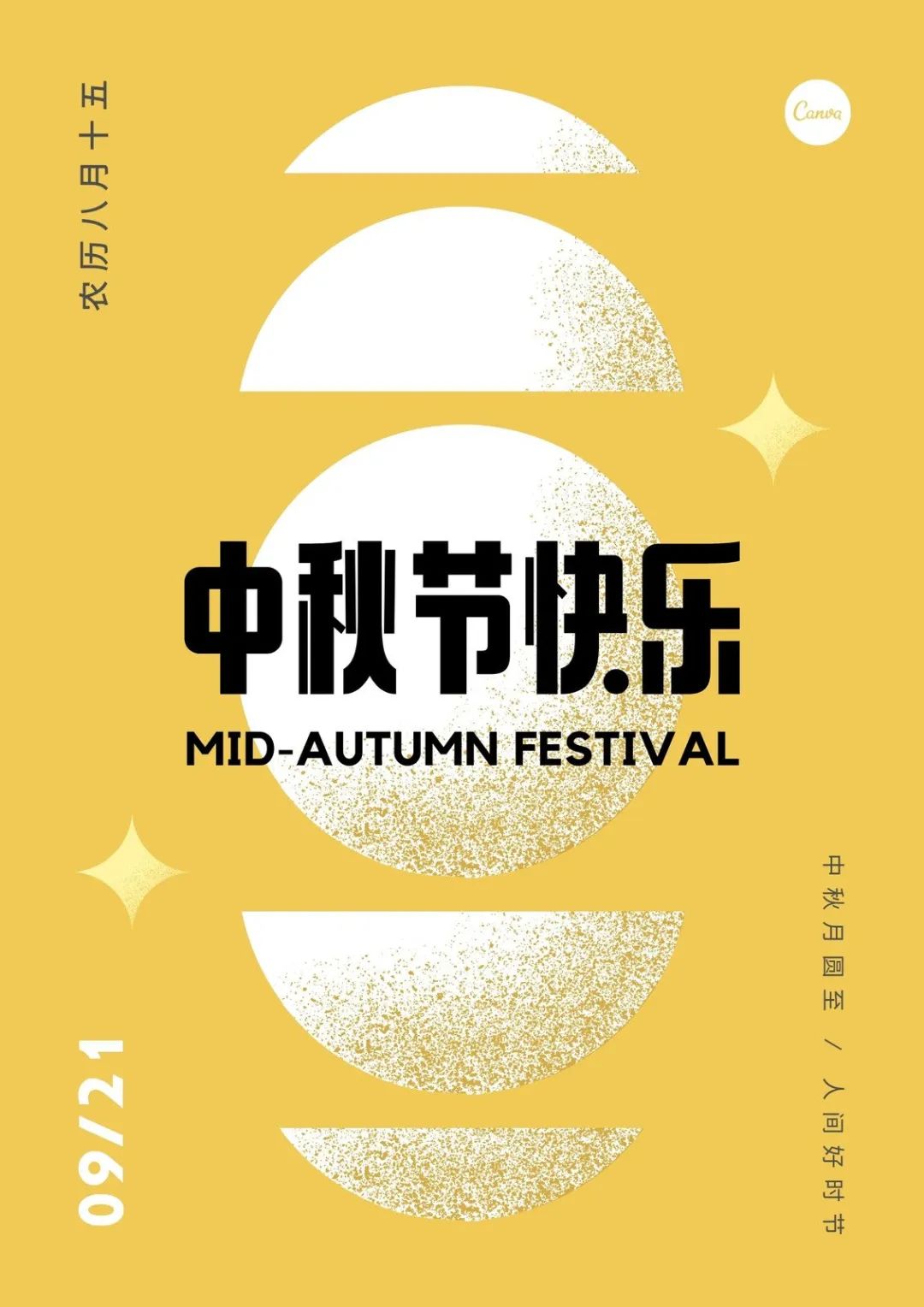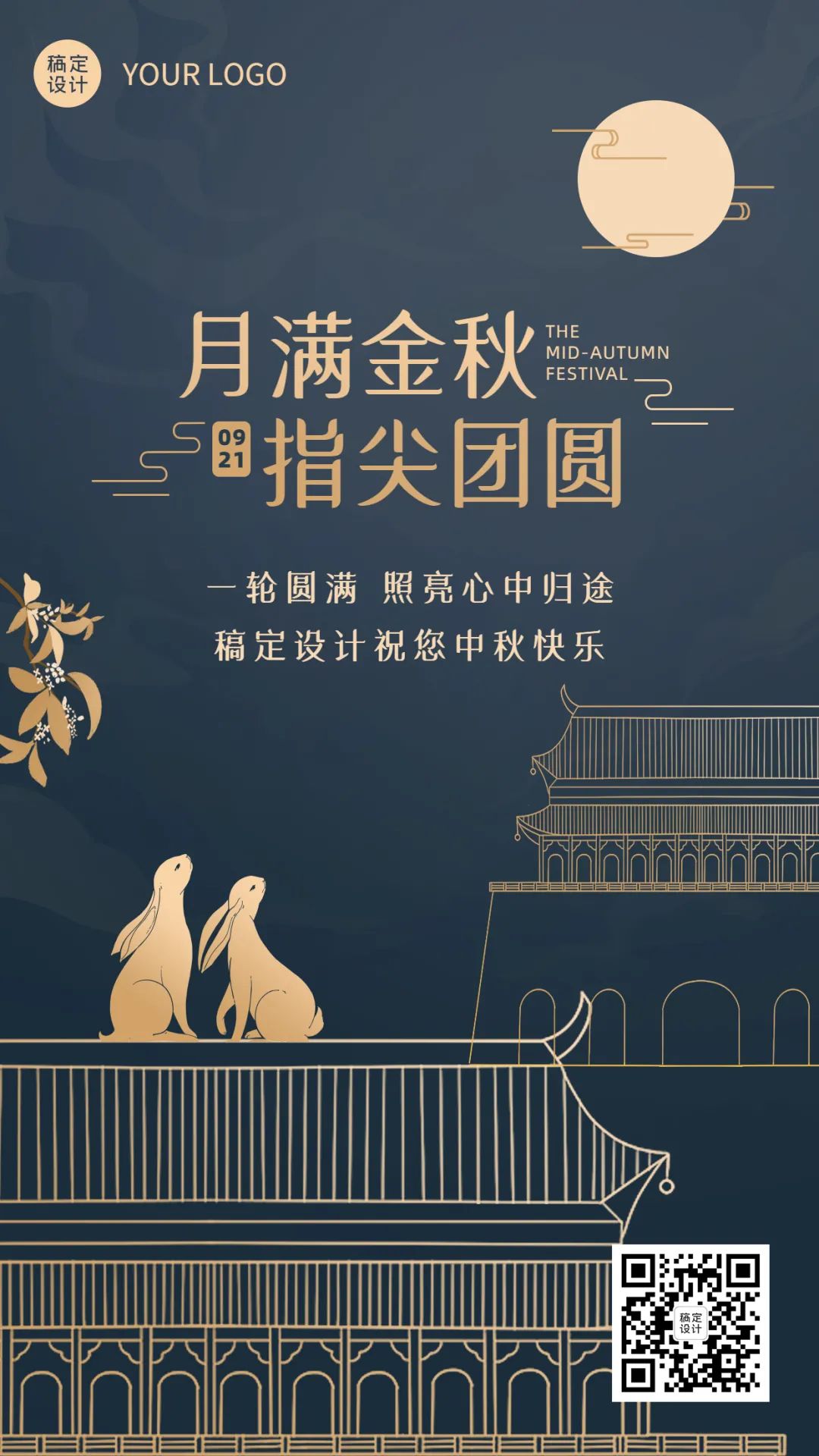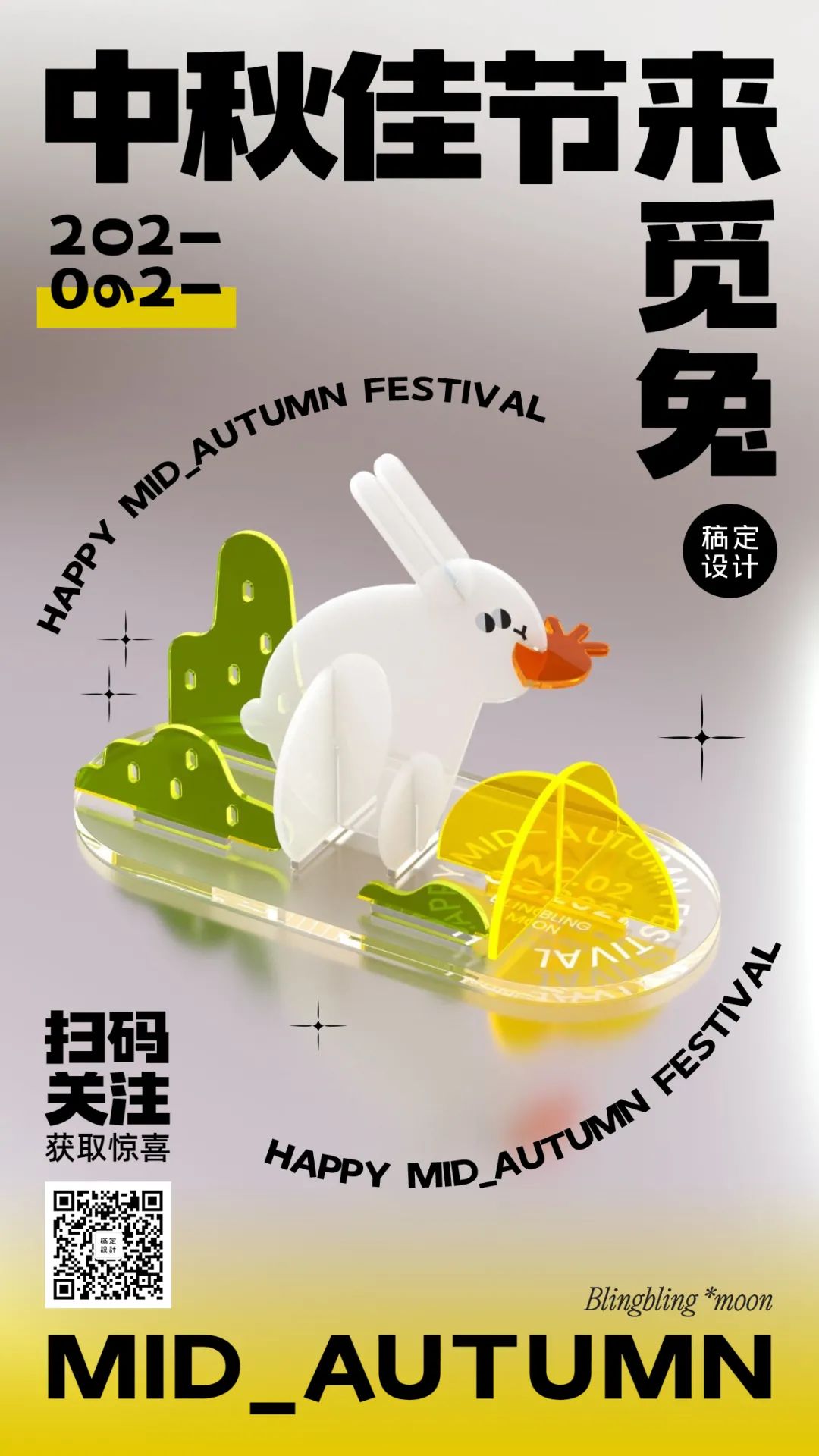
适合中秋国庆的字体大全
眼看着马上就中秋了,紧接着又是国庆,可是柚子却高兴不起来,一是抢不到北京环球影城的VIP门票(注定要家里躺平了),二是还有很多图要做啊(如果不想加班的话),想想就脑阔痛……
那说回马上就要交作业的中秋,如果你想走古典路线,可以选择传统的楷书、隶书、毛笔字等。
如果想别出心裁一点,可以选择更有个性的创意字体。
再看看字体的实际应用,立马更有感觉了~
▲点字简宋
▲字由芳华体
▲点字虎啸体
▲演示佛系体
▲三极花信简体
▲点字稻草人
▲点字墩墩体